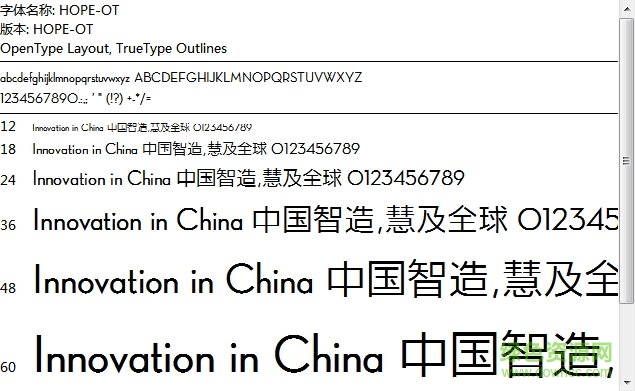
櫻木體是一款來源于努比亞社區(qū)分享的藝術(shù)字體,字庫全支持商標(biāo)符號(hào)、淘寶亂碼,讓你的文字更加端正好認(rèn),無過多的修飾,還原文字本身的質(zhì)樸之感,來綠色資源網(wǎng)下載試試吧!
櫻木體字體包含兩款字體,一款是原生態(tài)的簡潔版,一款是二次元美化后的海上自用版,但字體本身模板不變,線條清晰正直,讓文字也變得更加易于辨認(rèn),可以使用在多種領(lǐng)取,也可以作為你的手機(jī)字體。